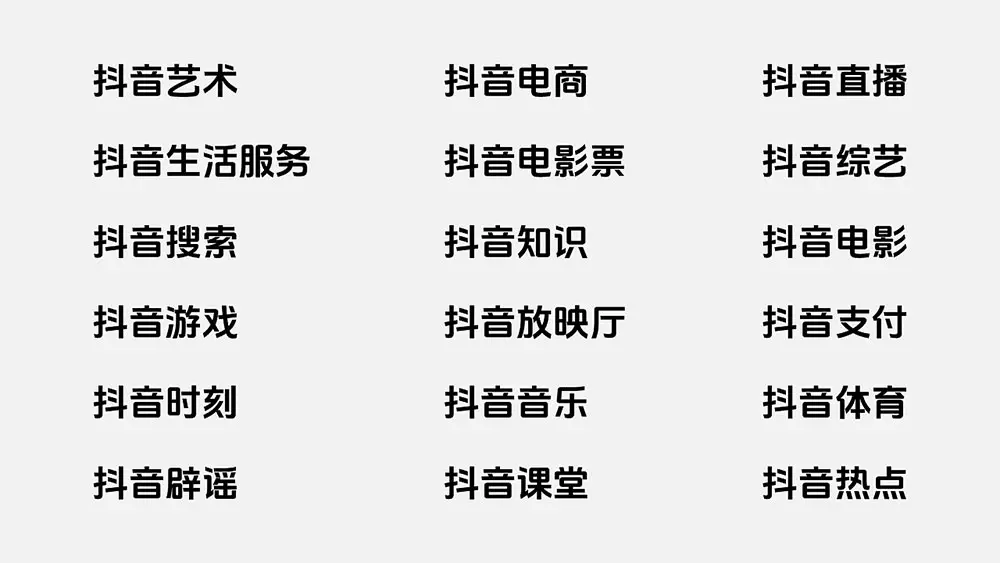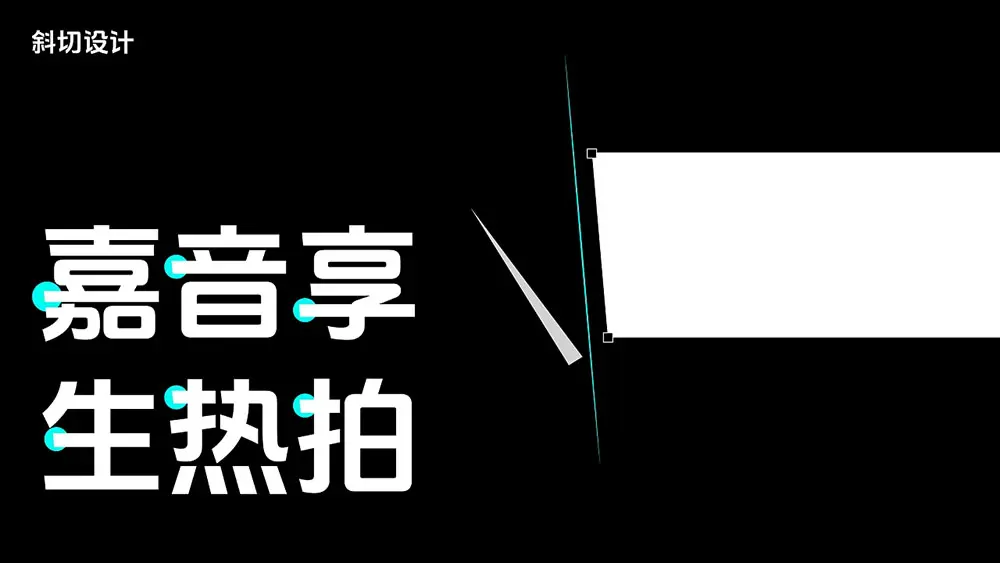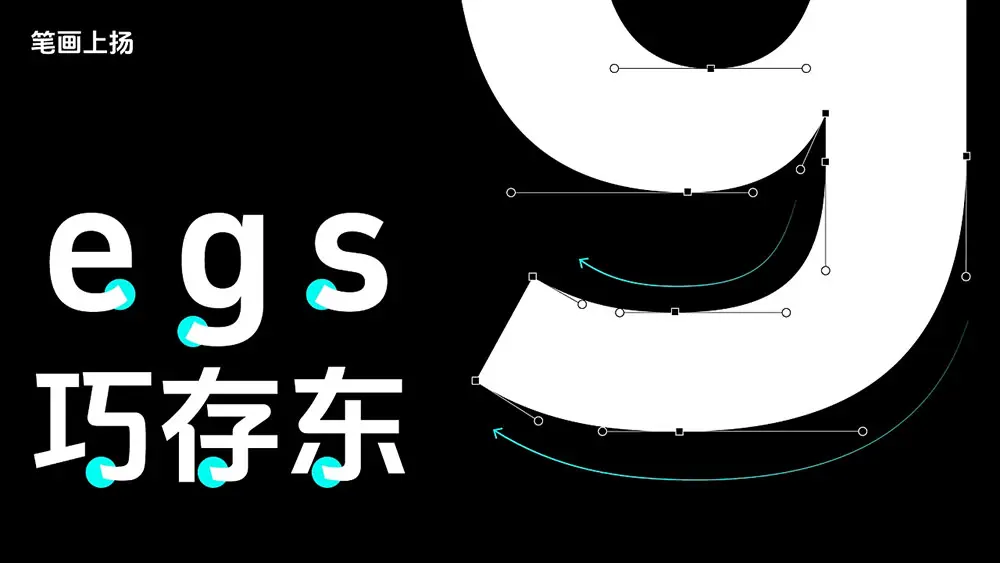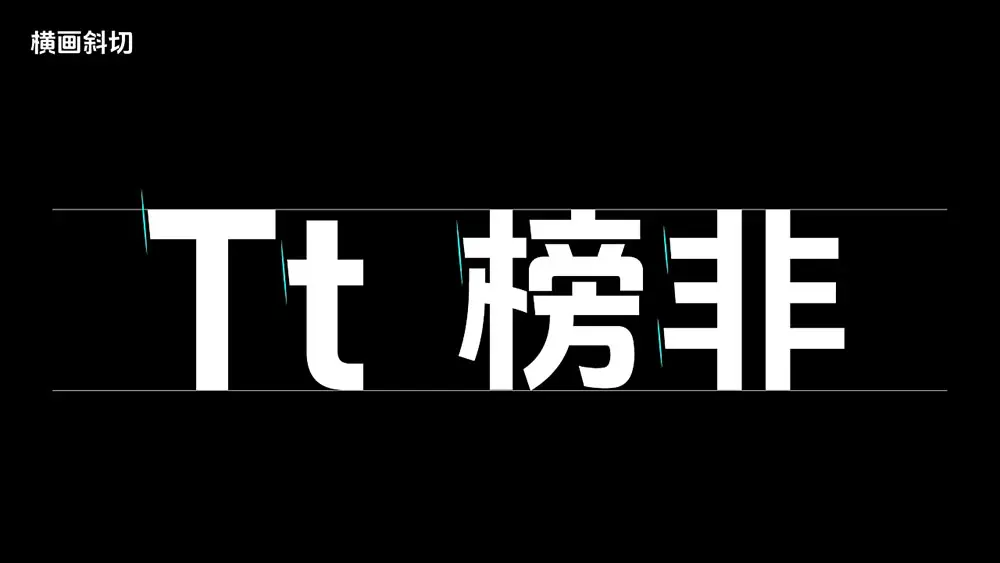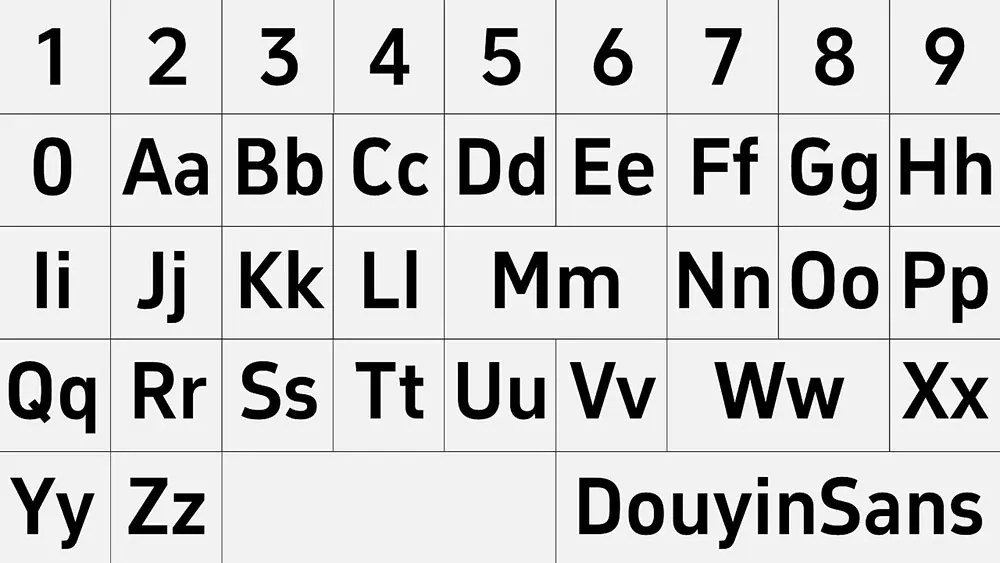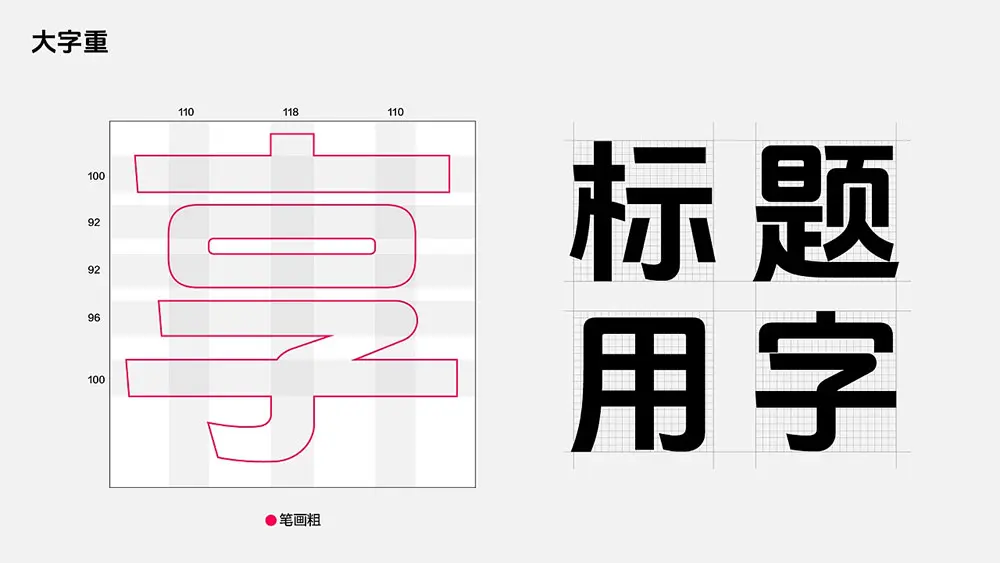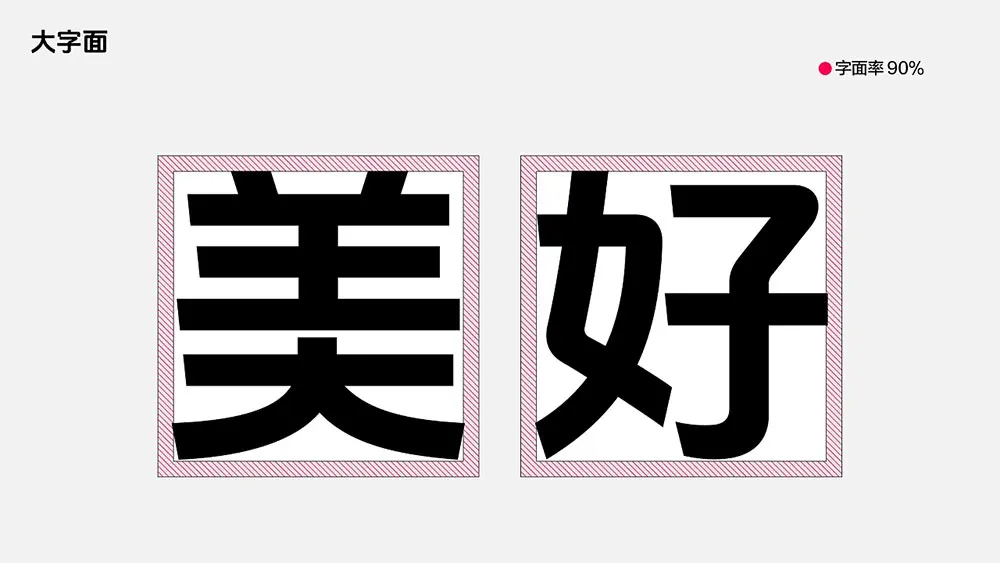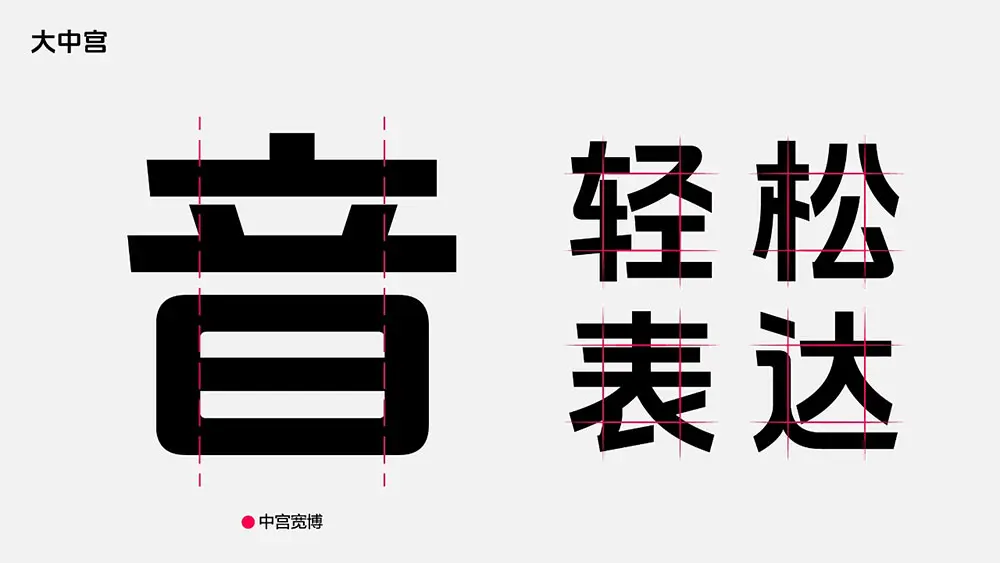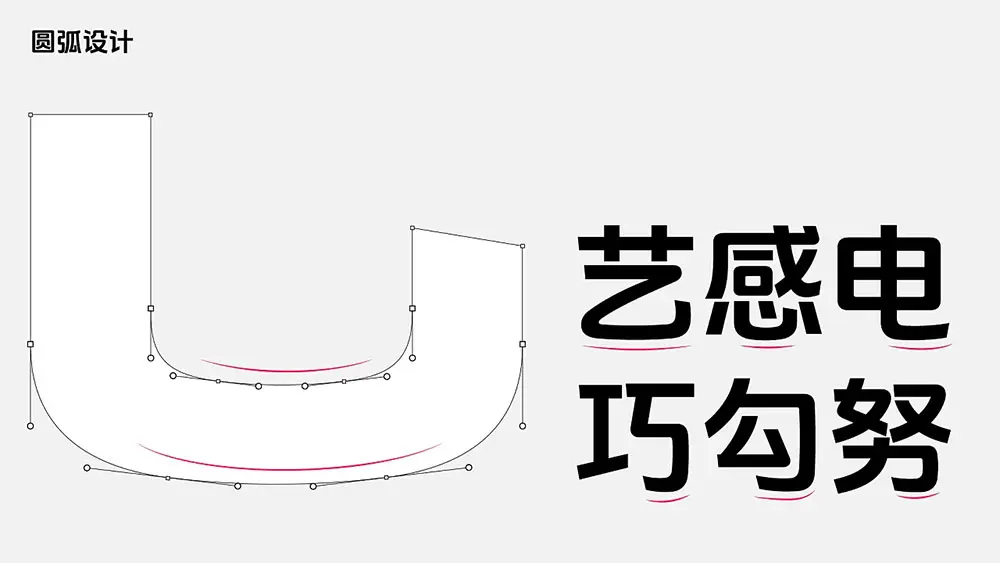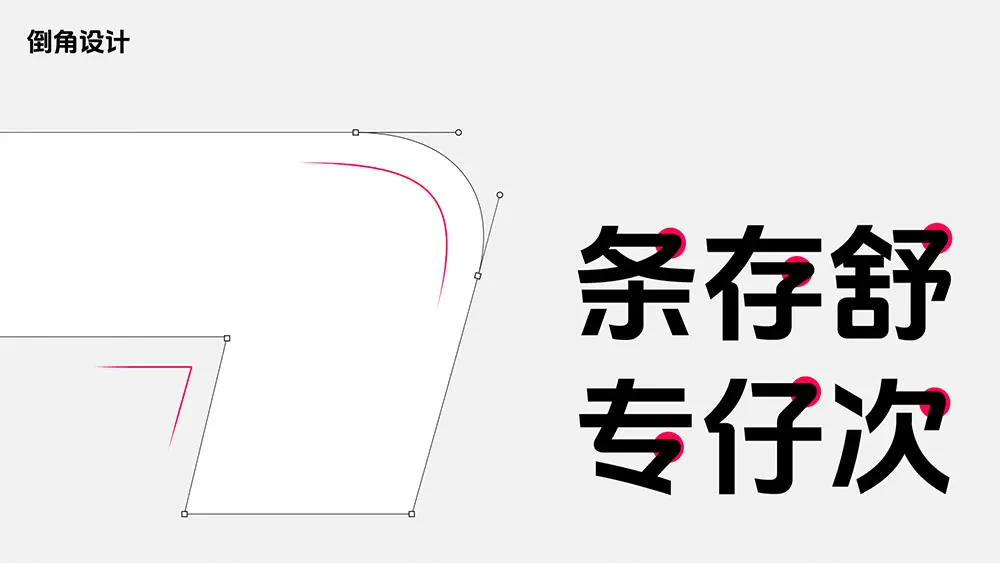
2023年,抖音已經從短視頻平臺發展為多體裁內容創作與分享平臺,將優質內容帶給用戶的同時,更鼓勵每一個人輕鬆創作與分享,去發現美好、傳遞美好。為了更好地傳播“記錄美好生活”的品牌理念,更好地滿足品牌長遠發展,打造優質的內容創作與產品體驗,抖音體驗設計中心與方正字庫聯合設計開發了一款簡潔大方、清晰易讀,同時兼具現代氣質與人文屬性的品牌定製字體——抖音美好體。
抖音美好體包含6763箇中文字符,682個西文及數字符號,執行國家GB2312-80簡體中文編碼字符標準。作為品牌標準字體,抖音美好體將會率先用於抖音及其子品牌中,助力品牌視覺形象的統一,提升品牌的官方性、權威感。
場景賦能,助力業務發展:為了更好地以品牌賦能產品與業務,滿足抖音端內不同場景的字體應用訴求,抖音體驗設計中心團隊將西文及數字字符拓展至5種不同粗細、寬窄,提升了字體與產品場景的適配度。除了全量上線抖音端內核心場景以外,抖音美好體已被廣泛用於抖音市場傳播場景,同時已內嵌於剪映、醒圖等產品,抖音美好體將不斷地助力業務發展。
方寸之間,塑造品牌差異:差異化的品牌視覺形象,有助於塑造差異化的品牌調性。抖音美好體通過字體骨架搭建、筆畫細節設計等細節,塑造出“沉穩內斂、自然舒適”的字體性格,與抖音帶給人們“輕鬆、自然、舒適”的產品體驗遙相呼應,傳遞出抖音獨特的品牌調性與感受。
抖音美好體提取了“抖音”logo字體簡約清新的風格特徵,為適應標題場景的使用,被打造為筆畫較粗的大字重字體;90%的大字面率,呈現出美觀大方、清晰易讀的視覺風格;大中宮設計,使得字體更加舒展飽滿,字體具有極強的識別特徵。
為構建品牌字體的獨特性,抖音美好體的筆畫細節採用了非常規的圓弧設計和倒角設計。彎勾筆畫採用大麴率圓弧曲線,均勻順滑的線條設計使得字體更流暢優美,更具視覺韌性。折筆筆畫則在平衡字體易讀性和識別度的基礎上,採用了內直外弧的倒角方式,傳遞出一種“剛柔並濟”的人文氣息。
書法融合,傳承傳統文化:書法是中國傳統文化的重要組成部分,筆畫、結構、佈局等元素都蘊含著豐富的文化內涵和審美價值。抖音美好體將傳統書法文化中的書寫感、流暢感與現代字體設計相結合,借鑑了行書中連筆書寫一氣呵成的精髓,形成獨特的連筆設計,將“靈動流暢、收放自如”的視覺體驗與抖音“輕鬆、自然、舒適”的產品體驗融為一體。
抖音美好體同樣借鑑書法中筆鋒的概念,將發筆時順勢落筆、筆鋒顯露在外的“露鋒”筆法,轉換為橫筆斜切的設計手法,在保留書寫感的同時,增加字體的視覺變化節奏。
中西匹配,統一視覺氣質:為了滿足抖音全生態全場景的標題使用需求,抖音美好體搭配了具有幾何風格的西文字符,字形簡潔幹練、現代時尚,同時在細節上延續了中文的圓弧及橫筆畫斜切的特徵,中西文匹配使用時呈現出一致的視覺氣質。